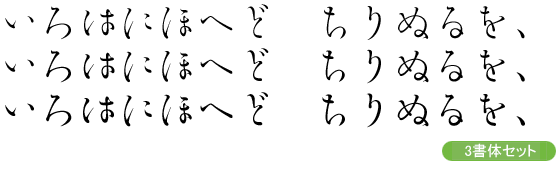
勢蓮明朝仮名ClassicOT-EL
SeiminKanaClassicOT-EL
「日本タイポグラフィ年鑑2001」受賞の仮名書体「勢蓮明朝-M」をブラッシュアップし、多ウェイト化や約物などの文字を拡張して制作された仮名書体。見出し書体としてのインパクトのみならず、可読性に優れたフォルムから、本文書体にも容易に利用できます。お得な8ウェイトセットもあります。